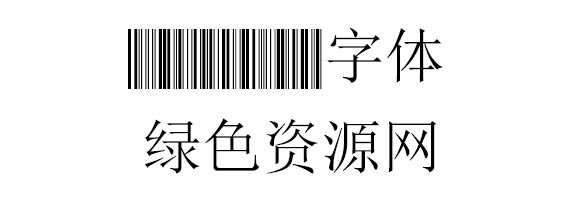
IntP72DlTt條碼字體
IntP72DlTt是一款端正美觀的條形碼字體,此款字體非常適合做產(chǎn)品包裝,本站還有很多其他條形碼字體供用戶(hù)選擇,需要的朋友來(lái)綠色資源網(wǎng)下載!
IntP72DlTt字體介紹
IntP72DlTt是我們生活中常使用的條形碼字體,給你展示的即時(shí)條形碼的樣式,可以使用在很多地方